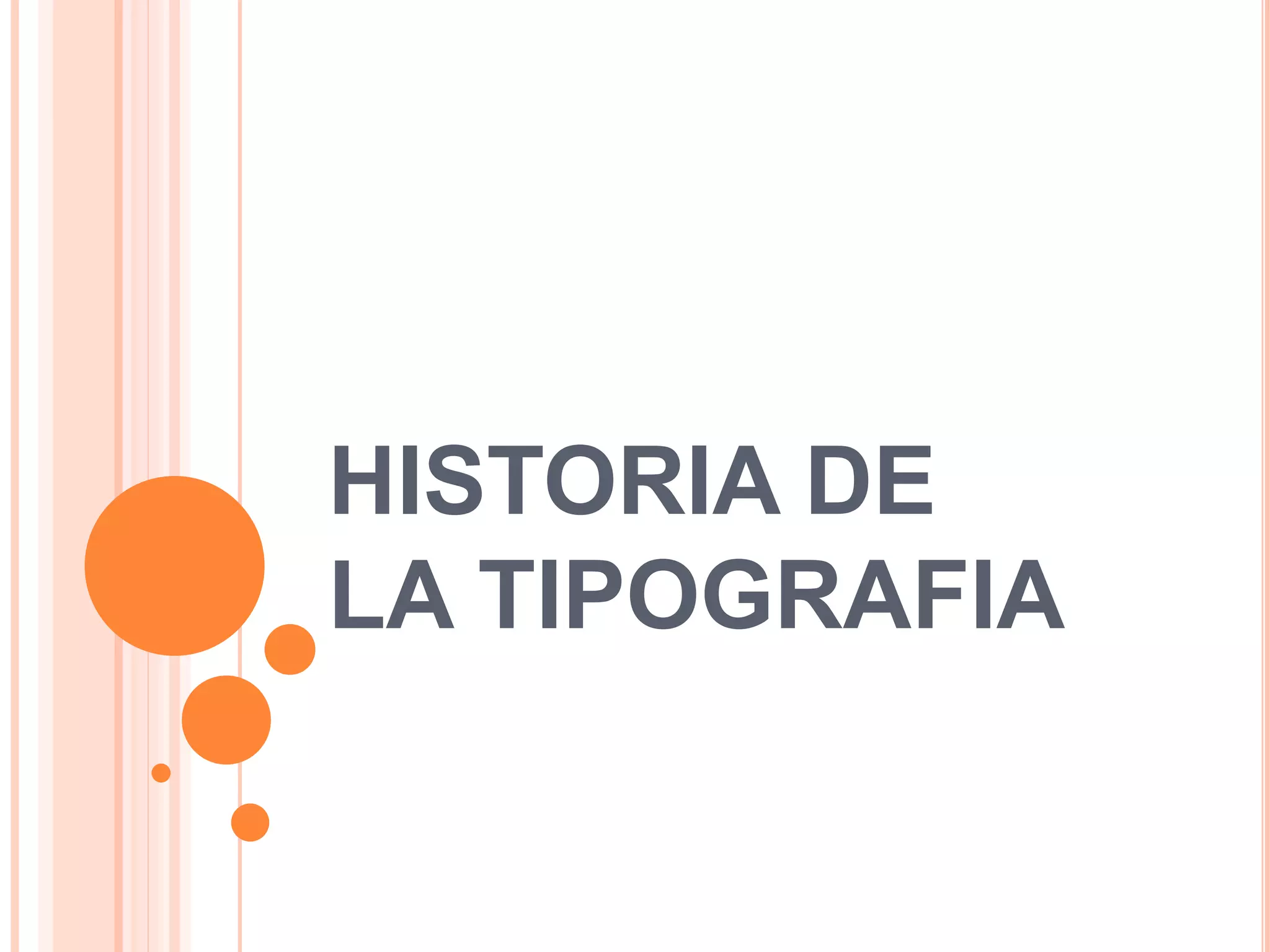
HISTORIA DE
LA TIPOGRAFIA
TIPOGRAFÍA
 Es el arte y el oficio que trata el tema de las
letras, números y símbolo de un texto impreso.
 El propósito específico es el de colocar las letras,
repartir el espacio y organizar los tipos con vistas a
prestar al lector la máxima ayuda para la
comprensión del texto escrito verbalmente.
• (Cullen, Kristin)
ORIGEN
 Esta relacionado con la caligrafía y los
manuscritos, que ya eran usados antes del año
2500.
 En la edad media la «industria editorial» se
centraba en los monasterios donde los libros eran
copiados a mano por monjes especializados,
llamados copistas; esta labor se hacía en el
scriptorium, en donde se copiaban los textos.
 Con el invento de la imprenta, durante el
renacimiento, la tipografía tomo una especial
relevancia, en esta época Johanes Gutenberg
imprimío su biblia de 42 líneas utilizando caracteres
del periodo gótico.
 En el año 1500, la imprenta ya se había difundido y
en Europa ya existían alrededor de 1100 imprentas
instaladas y funcionando.
TIPO Y CLASIFICACIÓN
 Se entiende por fuente tipográfica al estilo o
apariencia de un grupo completo de caracteres,
números y signos, regidos por características
comunes. Mientras que familia tipográfica, es un
conjunto de tipos basado en una misma fuente con
algunas variaciones, tales como por ejemplo el
grosor y la anchura, pero manteniendo
características comunes.
SERIF
 Las fuentes serif o de adorno, tienen su origen en el pasado,
cuando las letras se cincelaban en bloques de piedra, pero
era difícil asegurar que los bordes de las letras fueran rectos,
por lo que el tallador desarrolló una técnica que consistía en
destacar las líneas cruzadas para el acabado de casi todas
las letras, por lo que presentaban en sus extremos unos
remates característicos.
 Se subclasifican en las sig. Clases:
Romanas clásicas, Romanas de transición, Romanas de
antiguas o estilo viejo, Romanas Modernas o Didonas, De cuña
o glífico y Caligrafiadas.
SANS SERIF
 Estas fuentes están simplemente sin patines o pies, es decir,
no tienen remates en sus extremos. Hacen su aparición en
Inglaterra durante el siglo XIX. Entre sus trazos gruesos y
delgados no existe contraste, sus vértices son rectos y sus
trazos uniformes. Este tipo también llamado «Palo Seco» se
subclasifica en: De contraste, geométrica, grotesca,
humanista, informal, híbrida, de determinación redonda,
Bauhaus y ajustada.
 Ejemplos: Arial, Chicago, Mónaco, Tahoma,Helvética y
Verdana
MANUSCRITAS O SCRIPT
 Estas fuentes parecen cursivas o de caligrafía. En el diseño
de una presentación digital, estas fuentes se reservan para
acentuar el título principal, o la firma del autor, pues los trazos
más finos pueden desaparecer, comprometiendo la
legibilidad.
 Se subdivide en: Brush, caligráfica, canciller, casual, formal,
semi-formal, gráfico y mono línea. Entre otros ejemplos están:
Aelfa, Belphebe, Brush, Edwardian Script, English, Killigraphy,
Medieval Victoriana y Vivaldi.
FUENTES DE EXHIBICIÓN
 Son las de mayor atracción, la forma del carácter puede
sugerir una época o periodo de tiempo, otras otorgan mayor
personalidad.
 Subcategorias: Antigua, art Nouveau y art Deco, de
exhibición, Grune, de fantasía, de pixel, de arte pop, de
esténcil y la más reciente «mass media».
 Ejemplos: Terminator, Star Wars, Final Frontier y Jokerman,
en su gran mayoria creadas por la industria del
entretenimiento, el arte y la tecnología.
DE SÍMBOLOS E IMÁGENES (DINGBATS &
DINGFONTS)
 Incluyen caracteres y formas no encontrados en alfabetos
tradicionales (dingbats & dingfonts), diseños que contienen
juegos de caracteres de matemáticas, fonéticos y otros usos
especializados.
 Son fuentes integradas por símbolos, muestras, logotipos,
ornamentos, imágenes, y otros caracteres no alfabéticos.
 Se utilizan para enfatizar, para viñetas y decoraciones.
FAMILIAS Y FUENTES
TIPOGRÁFICAS
 Se entiende por fuente tipográfica al estilo
o apariencia de un grupo completo de
caracteres, números y signos, regidos por
características comunes. Mientras que familia
tipografica, es un conjunto de tipos basado en una misma fuente con
algunas variaciones, tales como el grosor y la anchura, pero
manteniendo rasgos comunes.
 Además de la clasificación y sub- clasificación por familia
tipográfica, existe una versión, ampliada de las mismas, con
variaciones como: Serif Slab, Sans Serif tensionado, tipografía
monoespaciada, ultra condensada, gótica.